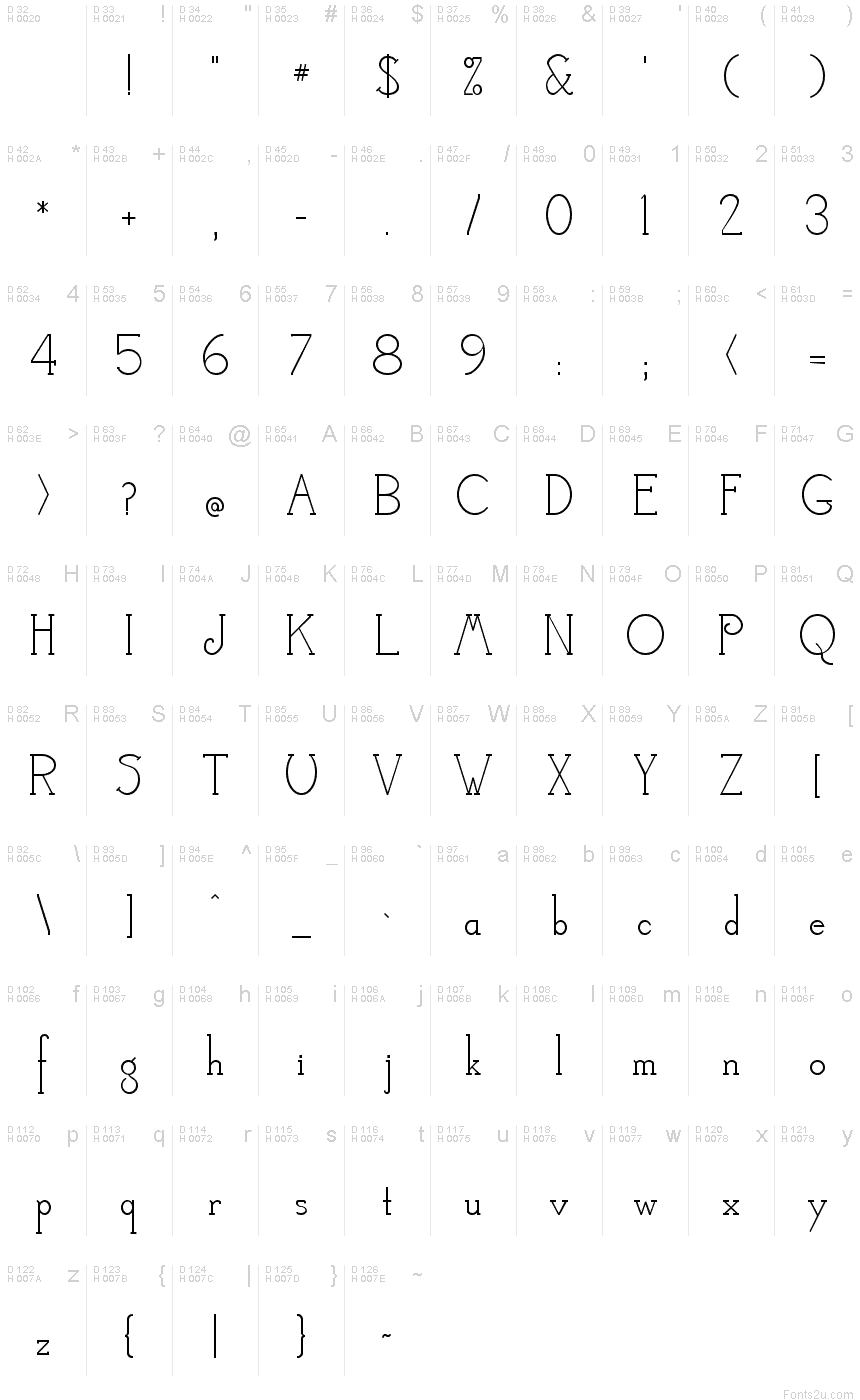
Camelot MF, stworzony przez Ricka W. Muellera, to darmowy krój pisma w stylu retro, wyróżniający się smukłą elegancją, która przywodzi na myśl zarówno baśniowy klimat, jak i butiki z połowy ubiegłego wieku. Ultracienkie kreski, duża ilość światła między znakami oraz połączenie obłych pętli z ostrymi kątami nadają każdemu słowu wyważony, ręcznie kreślony wdzięk, przypominający pismo wykonane precyzyjnym piórem technicznym.
Ten darmowy font świetnie sprawdza się na okładkach książek fantasy, plakatach w stylu vintage, w menu koktajlowych, ulotkach teatralnych, na opakowaniach produktów butikowych oraz w kreatywnym brandingu. Stosuj Camelot MF w większym rozmiarze, aby zachować wyrazistość jego delikatnych linii; w tekście głównym połącz go z prostym, kontrastowo subtelnym krojem bezszeryfowym, aby to ozdobne litery pozostały w centrum uwagi.